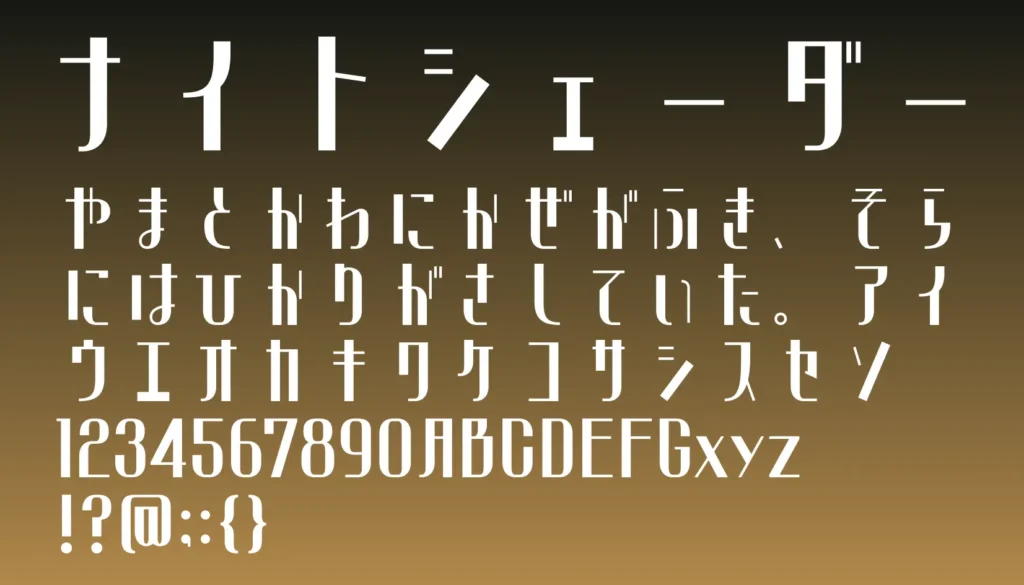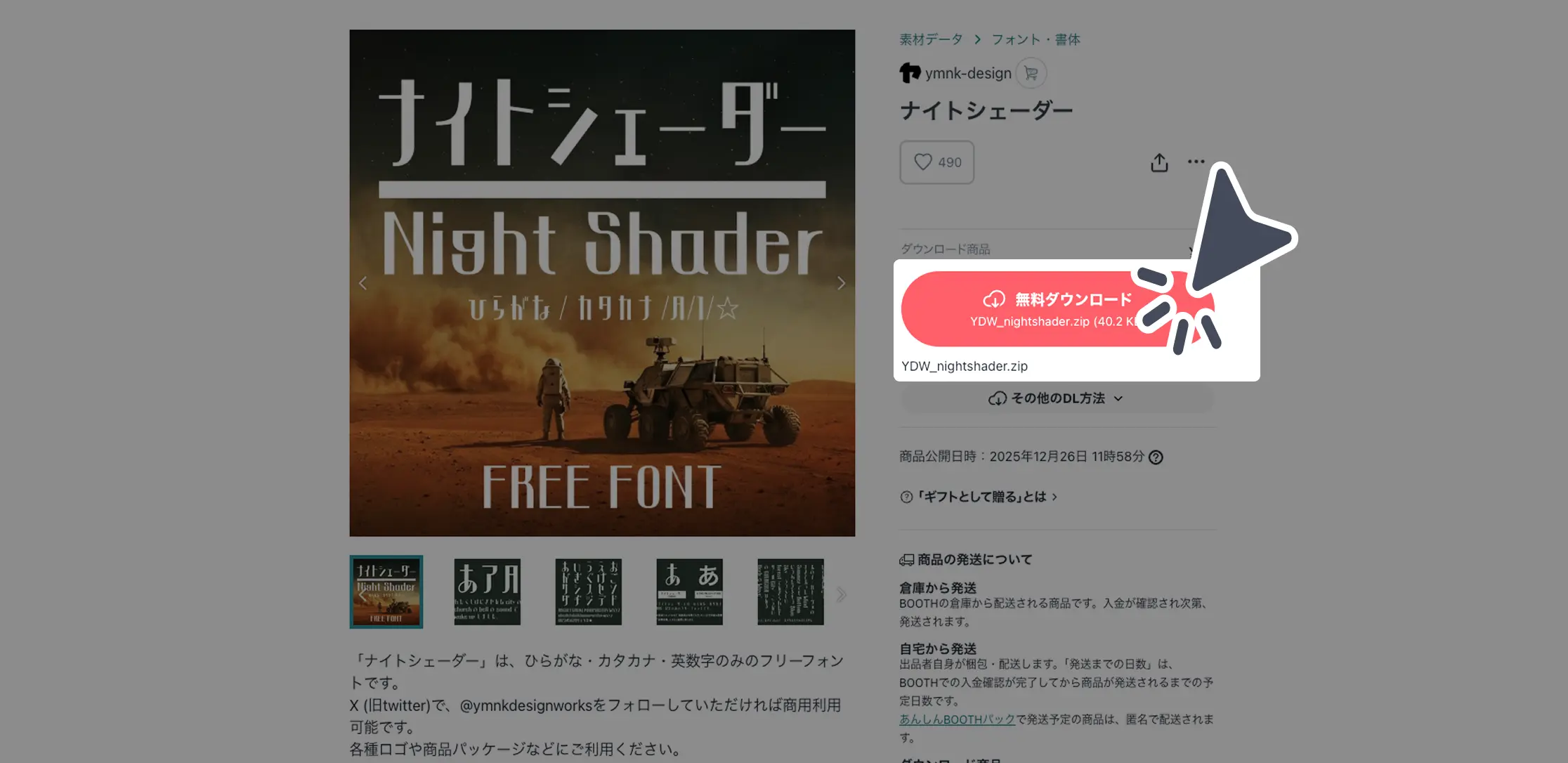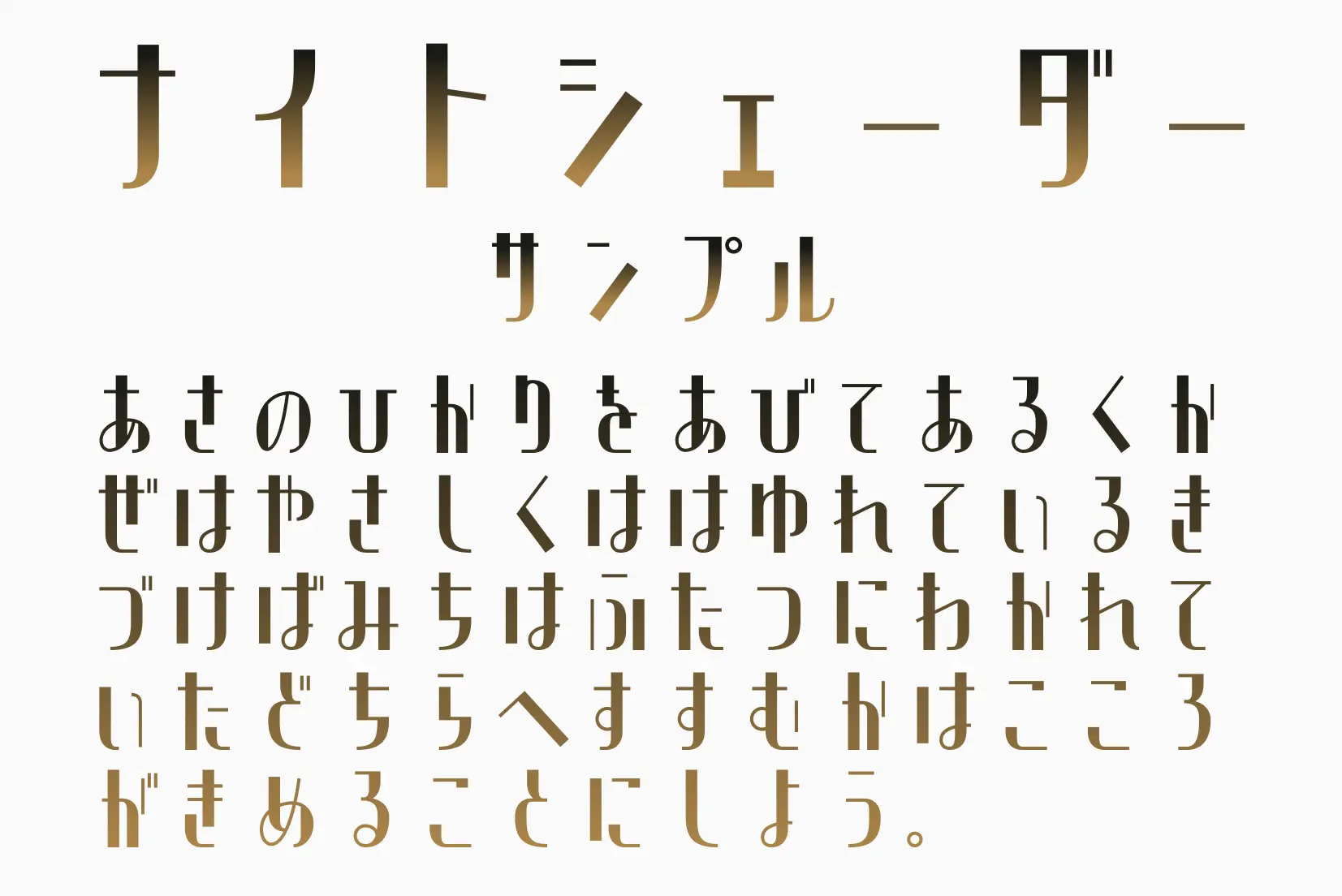
ナイトシェーダーは、シャープさと遊び心を両立したデザイン書体。直線的なラインをベースにしながらも、どこかポップで軽快な雰囲気があり、ロゴやタイトルなど視線を集めたい場面にぴったりです。クセは強すぎず、アイキャッチ用途にも扱いやすいのが魅力。パッケージやサムネイル、SNS用ビジュアルにも相性が良く、ひと味違うアクセントを加えたいときに活躍してくれるフォントです。
ナイトシェーダー